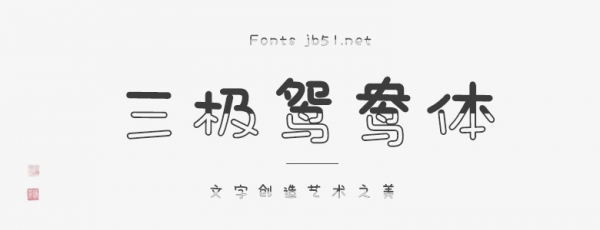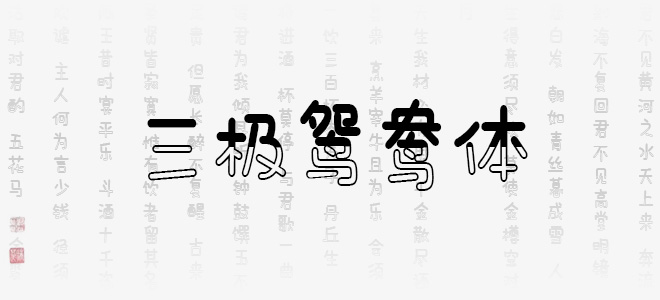
c設(shè)計(jì)比較自由但保持統(tǒng)一性,字與字之間的統(tǒng)一性是由上半部分黑色和下半部分白色組成,保持一種統(tǒng)一的變化規(guī)則,讓人有種直觀舒服的感受。在設(shè)計(jì)中應(yīng)用十分廣泛,字形飽滿圓潤(rùn),輪廓略顯臃肥,整體個(gè)性明快可愛(ài)。適用于少兒類讀物、書(shū)刊、品牌廣告、包裝設(shè)計(jì)以及社交網(wǎng)絡(luò)個(gè)性化用字。
三極鴛鴦體